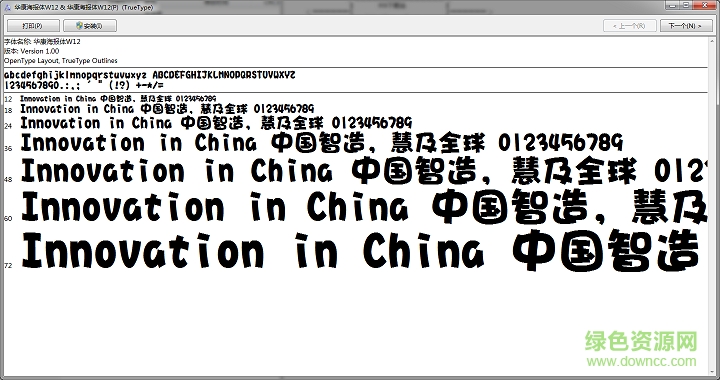
dfhaibaow12 是什么字体?dfhaibaow12 简体又叫华康海报体w12字体,是一款非常适合用于海报设计广告字体,饱满美观,活泼有趣,有需要者欢迎免费下载!
dfhaibaow12字体特色
专为海报标题而设计的字体,浑厚、沉稳中,又显现出独特的活力。活泼的骨架融合饱满的笔划,使这套字体相当适合为标题所用,如广告传单、海报和招牌等。